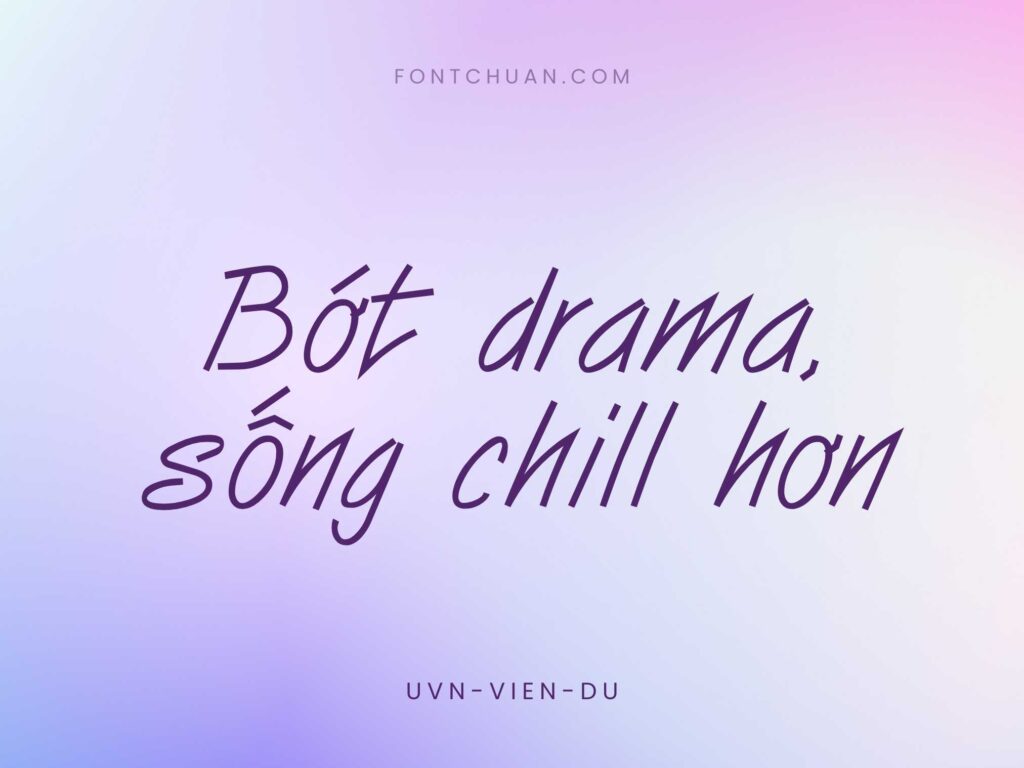
Font UVN Vien Du Việt Hóa
UVN Viễn Du là một phông chữ thư pháp mang phong cách nghệ thuật viết tay truyền thống. Được thiết kế với các nét bút lông mềm mại và uyển chuyển, phông chữ này tạo nên sự thanh thoát và tinh tế cho các tác phẩm thiết kế. UVN Viễn Du hỗ trợ đầy đủ các ký tự tiếng Việt, giúp người dùng dễ dàng sử dụng trong các dự án sáng tạo liên quan đến văn hóa Việt Nam.
Với thiết kế độc đáo và nghệ thuật, UVN Viễn Du phù hợp cho các ứng dụng như thiệp mời, tiêu đề sách, thiết kế logo và các ấn phẩm nghệ thuật. Trong lĩnh vực sự kiện, phông chữ này có thể được sử dụng trong các dịp như lễ hội, lễ cưới và các sự kiện văn hóa. Ngoài ra, UVN Viễn Du còn là một Font chữ ảnh cưới lý tưởng, giúp trang trí album ảnh cưới, thiệp cưới hoặc các sản phẩm kỷ niệm, mang đến không gian lãng mạn, tinh tế và nghệ thuật cho các thiết kế. Nó cũng thích hợp cho các ngành nghề như thiết kế đồ họa, nghệ thuật trang trí và xuất bản.